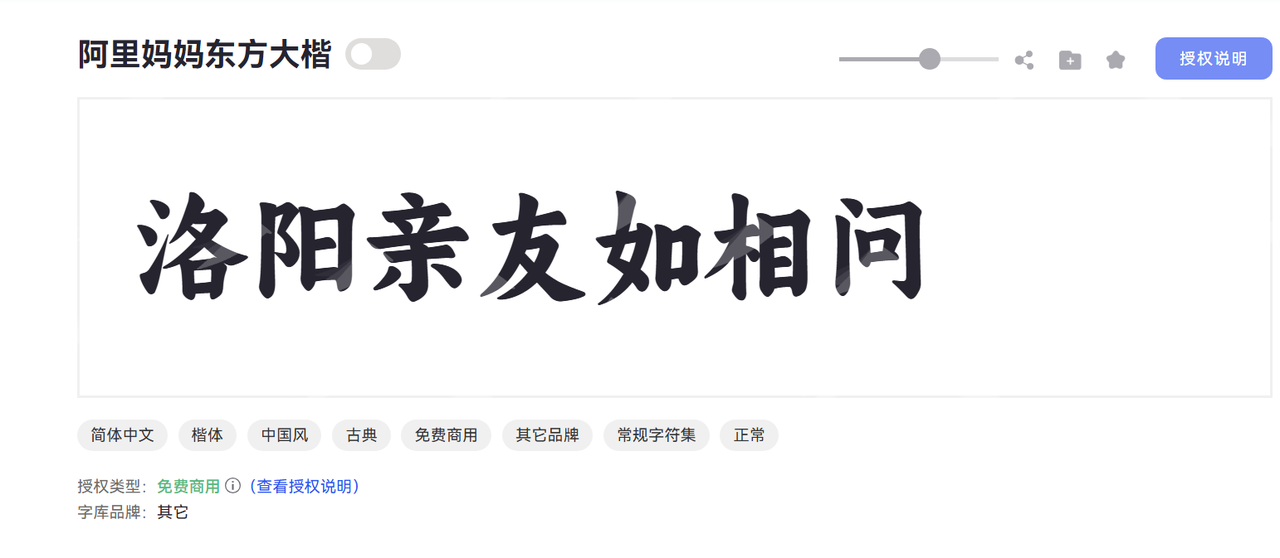
不用找了 这几个阿里免费字体网站就够了!
做设计、剪视频、运营账号时,总被字体问题难住?要么觉得免费字体不好看,要么担心随便用字体侵权吃官司,翻遍全网找资源还总踩坑。其实根本不用这么麻烦,今天就给大家整理了几个阿里系的免费字体网站,每一个都经过实测,用过的设计师都说香,不管是新手还是老手,收藏这篇就够了!
一、字由网——阿里系字体用法天花板
字由网作为国内知名的字体管理与应用平台,堪称阿里系字体的“最佳搭档”,在这里可以一键找到所有阿里系免费商用字体,无需复杂操作就能快速应用于各类创作场景,堪称阿里系字体用法的天花板。
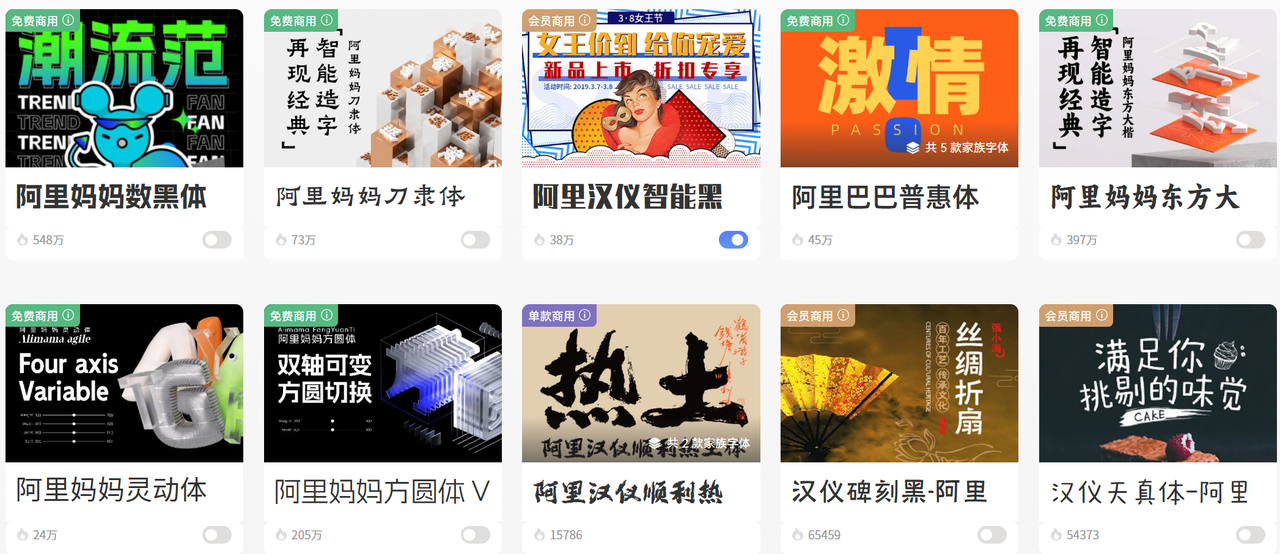
如果需要国风、书法风格的字体,阿里妈妈东方大楷绝对是首选,在字由网的国风创作场景中使用率极高。这款字体基于颜真卿的多宝塔碑算法生成,后期经过设计师优化,还原了传统书法的书写韵味。
阿里妈妈灵动体是阿里系免费字体中唯一一款专属英文字体,也是一款西文四轴可变字体,在字由网的双语排版场景中使用率极高,彻底解决了英文免费字体质感不佳的问题。
阿里妈妈刀隶体是一款极具个性的复古隶书字体,打造出兼具传统韵味和现代设计感的字体,在字由网的复古风格创作中十分热门,满足日常复古场景创作需求。
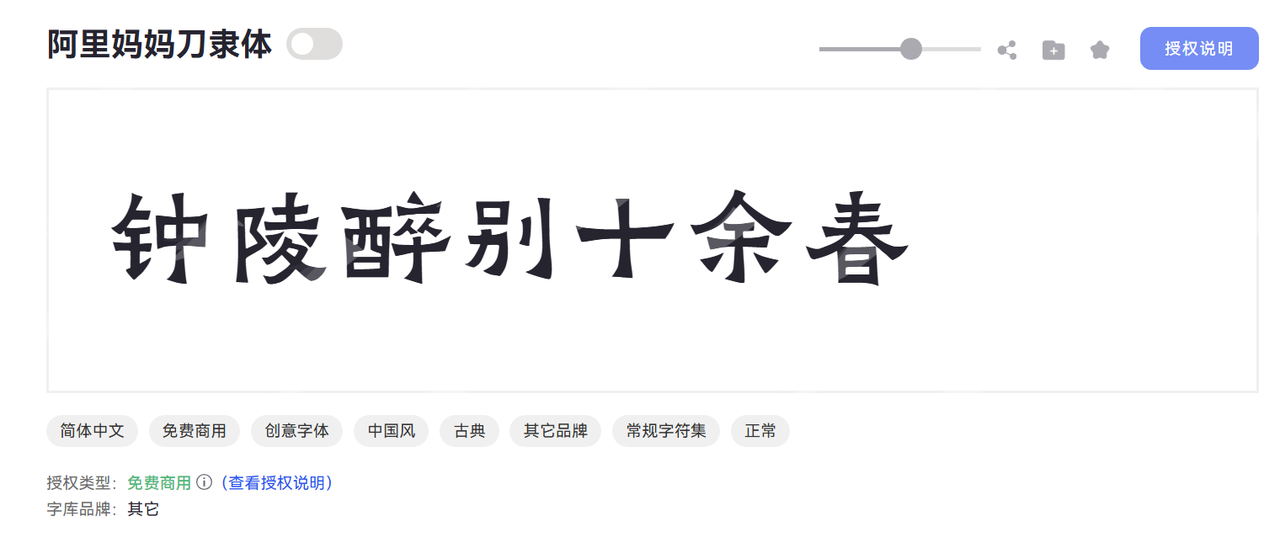
二、阿里字体官方平台——普惠字体源头站
作为阿里字体的官方源头平台,这里是获取阿里巴巴普惠体、阿里妈妈灵动体等官方字体的首选渠道。所有字体均免费商用,授权信息直接由阿里官方背书,完全无需担心侵权问题。尤其是阿里巴巴普惠体3.0版本,适配新国标且覆盖海量生僻字,不管是正式文档排版还是商业物料设计都能hold住;阿里妈妈方圆体作为双轴可变字体,可在方体与圆体间自由切换,粗细也能精准微调,创意设计场景下实用性拉满。
三、猫啃网——阿里系免费字体宝藏库
虽非阿里直接运营,但猫啃网早已与字由网达成深度合作,成为阿里系免费字体的重要收录平台。它以严苛的版权核验标准闻名,收录的上千款阿里系字体都标注清晰授权信息,还支持在线开具授权证书,客户索要版权证明时直接下载即可。网站分类极细,手写体、艺术体、书法体等一应俱全,想找小众有设计感的阿里系字体,来这里准没错。
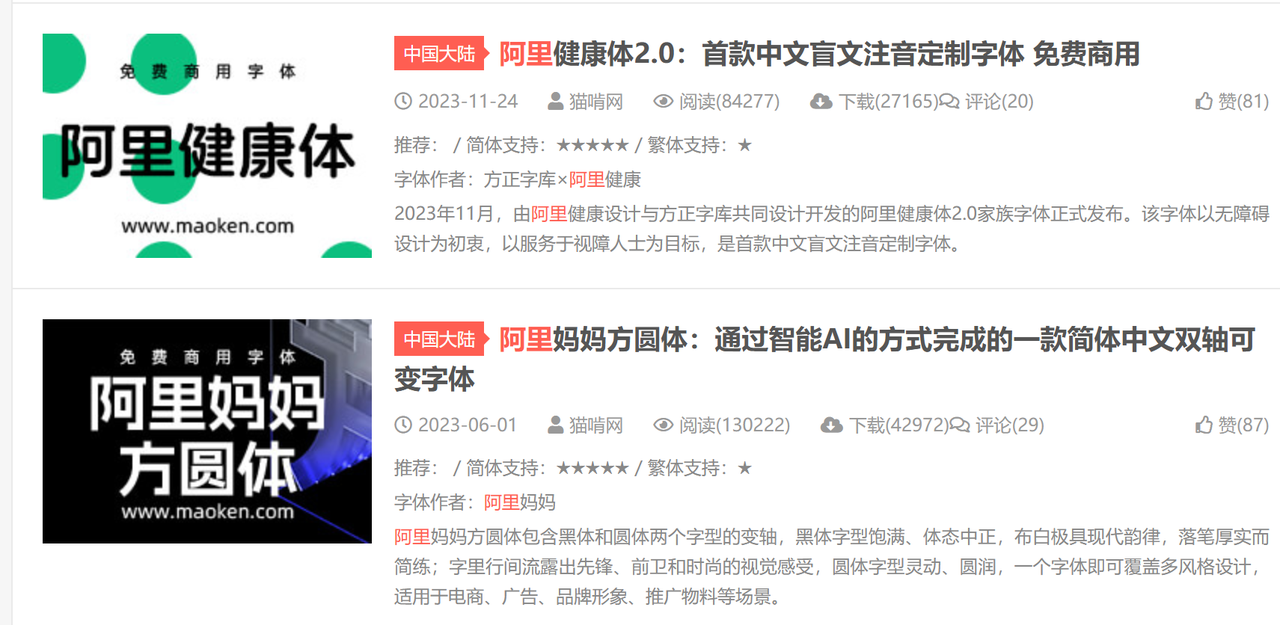
四、Pixso字体库——在线设计用字终点站
对于需要在线协作设计的团队来说,Pixso字体库堪称刚需神器。它内置大量免费商用的阿里系字体,更核心的优势是支持团队字体库同步——和同事协作时,再也不用担心因本地字体不同导致设计稿变形。注册即可免费使用,还配套丰富设计素材,从选字体到做设计一站式完成,新手也能快速上手,完美适配线上设计全流程。